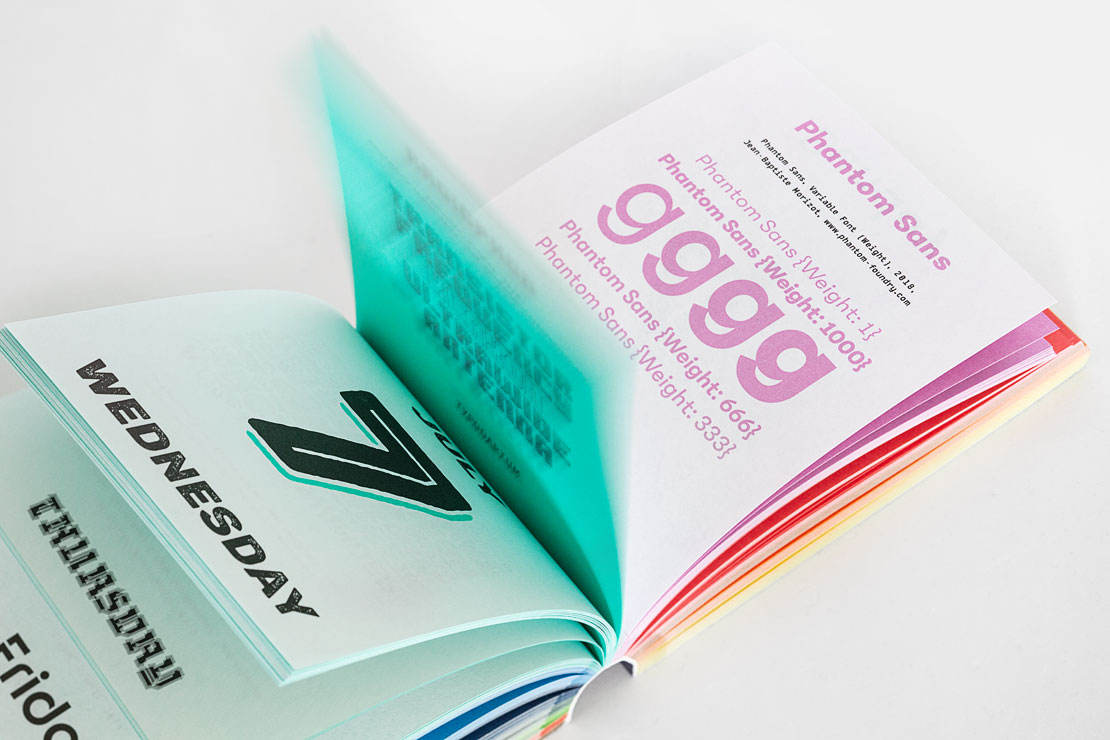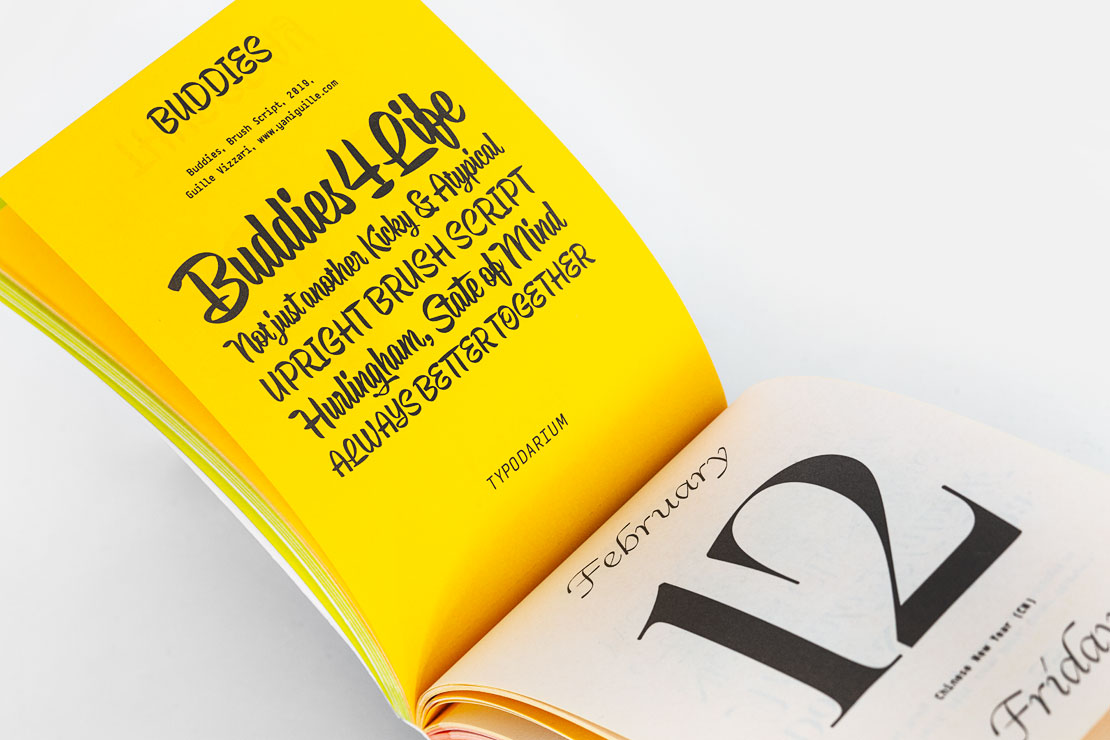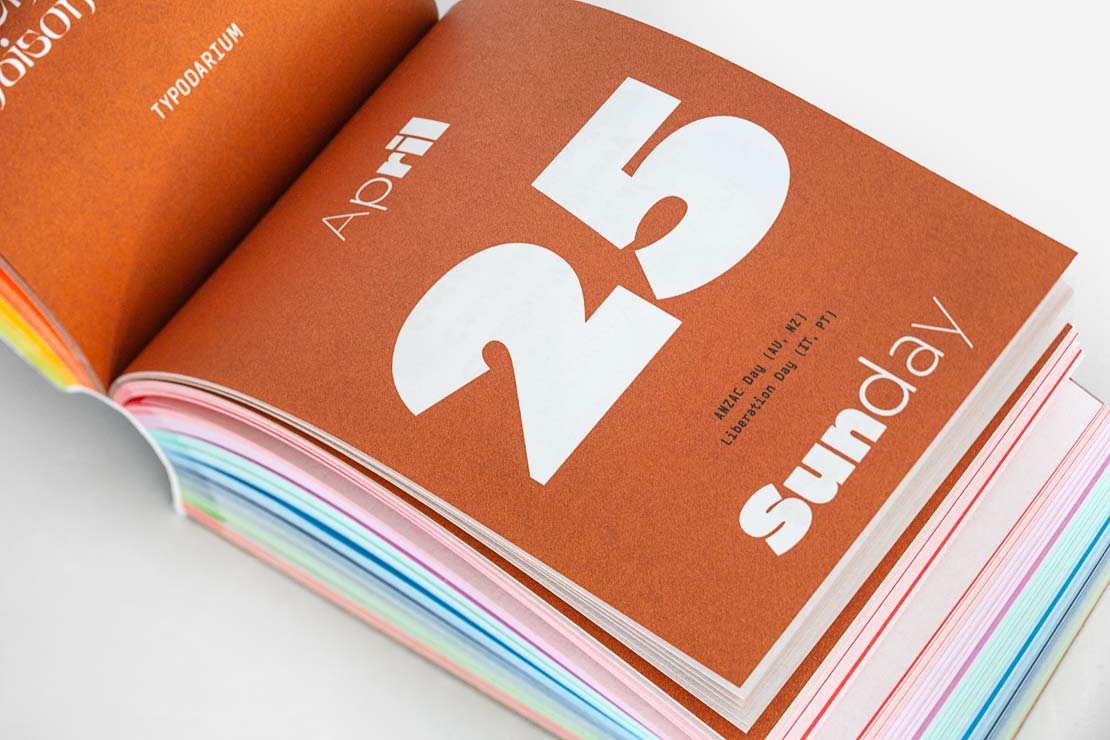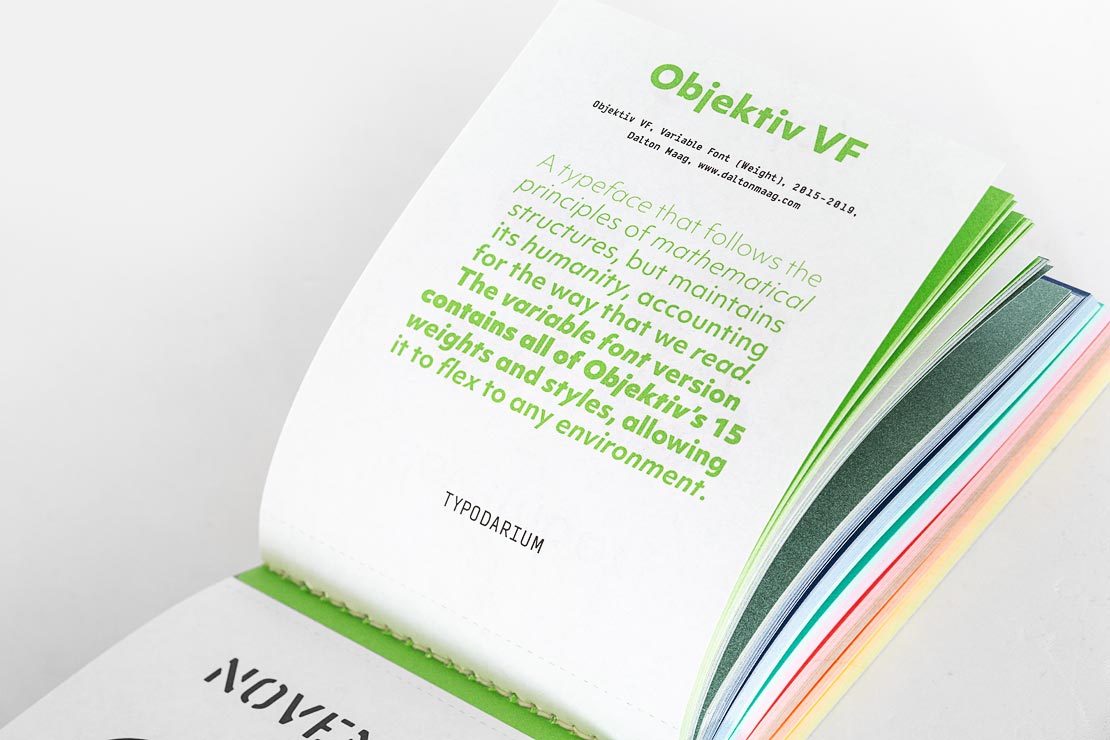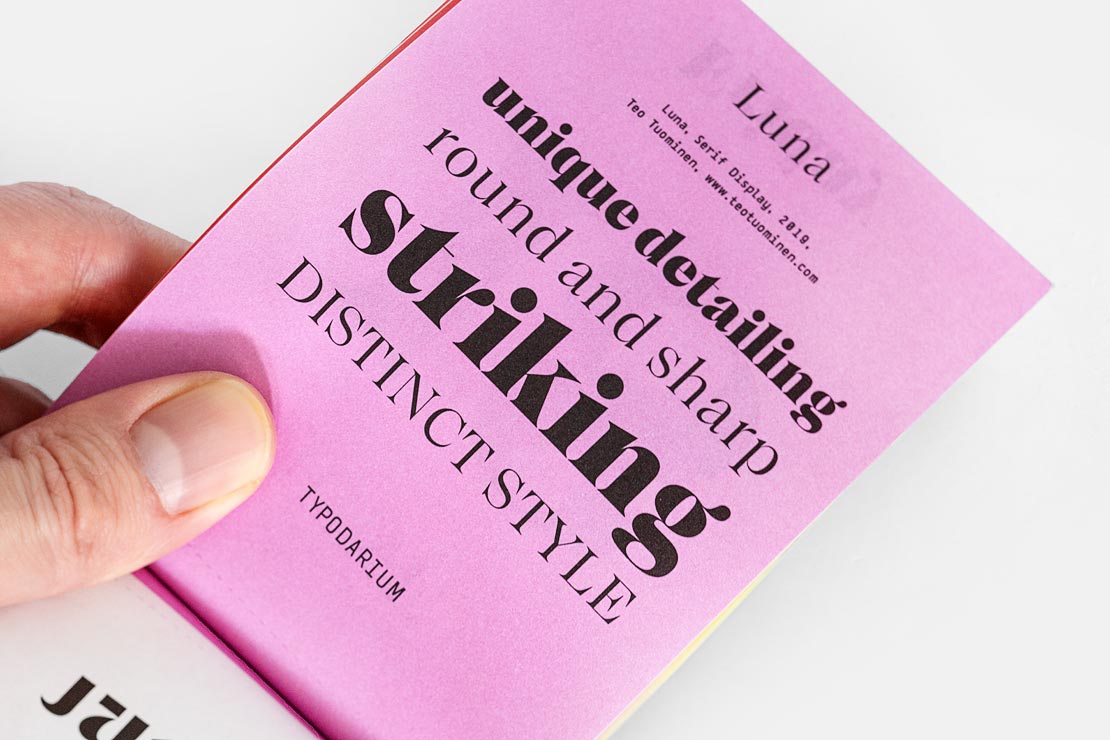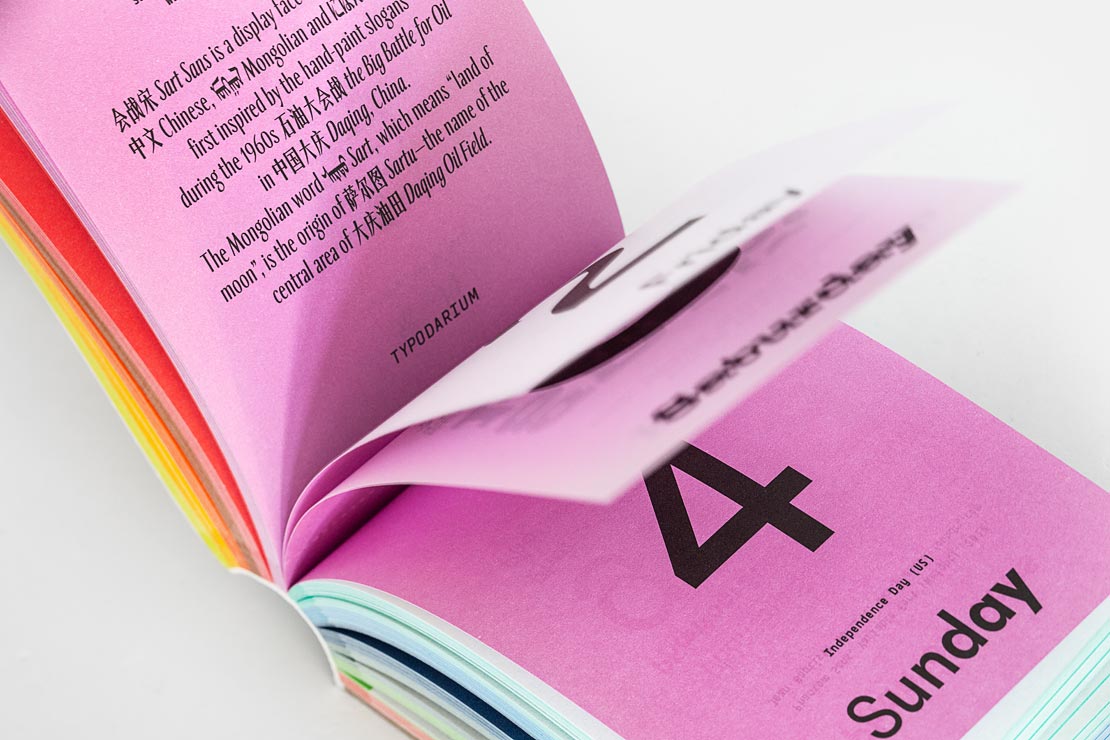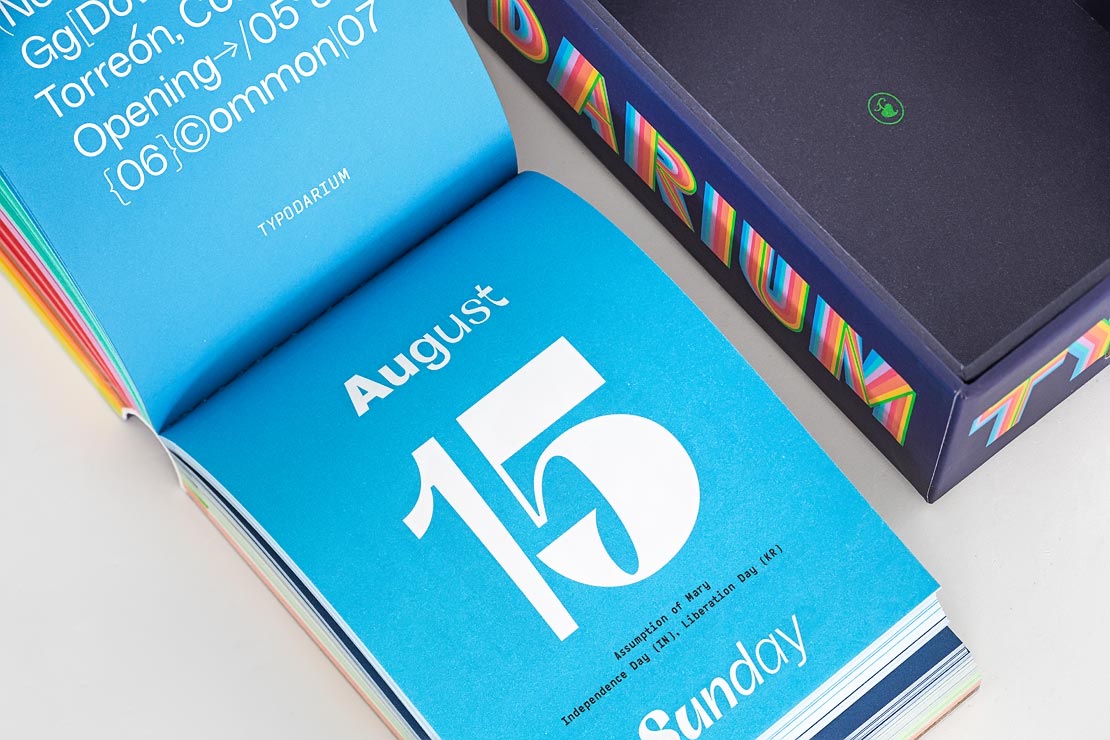
Typodarium: Typografischer Abreißkalender für 2021
Das »Typodarium« für 2021 ist da. Raban Ruddigkeit und Lars Harmsen stellen in ihrem Abreißkalender 365 frische Fonts für das kommende Jahr vor.
Diesmal präsentiert sich der Schriftenkalender in 12 fröhlichen Farben. Tag für Tag zeigt das Typodarium 2021 eine neue Schriftart, die es zum Entdecken gibt. So kommt man auf insgesamt 365 Schriften von 256 Designern aus 33 Ländern.
Schriftarten im Typodarium 2021 Kalender entdecken
Auf den Tagesblättern des Typodarium 2021 sind jeweils Datum, Wochentag und Feiertage vermerkt. Die Rückseiten zeigen zudem die jeweils verwendete Schriftart bzw. deren Ausbaugrade. Weitere Informationen zu Designer, Entstehungsjahr und den Bezugsmöglichkeiten findet man dort ebenfalls vermerkt.
Eine Besonderheit gibt es auf den „Sonntagsblättern“ zu sehen: einer von insgesamt 52 sogenannten „Variable Fonts“ wird jeweils am letzten Wochentag vorgestellt.
Als praktisch erweist sich die mitgelieferte Box. Diese kann zum Sammeln von bereits abgerissenen Kalenderseiten verwendet werden. So entsteht nach und nach ein Musterbuch mit den ganz persönlichen Schriften-Highlights.